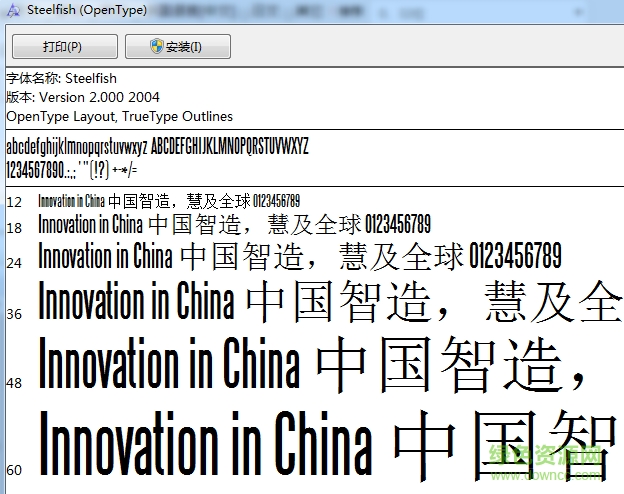
Steelfish英文字體
Steelfish字體是英文字體庫(kù)中的個(gè)性字體,字體非常纖細(xì),但卻極具個(gè)性,讓人能夠留下深刻印象,歡迎大家來(lái)綠色資源網(wǎng)下載使用吧!
Steelfish字體
Steelfish字體是一款個(gè)性英文字體,字體能夠幫助用戶體現(xiàn)自己的個(gè)性,彰顯不一樣的用途,有需要的朋友就趕快來(lái)綠色資源網(wǎng)下載吧!